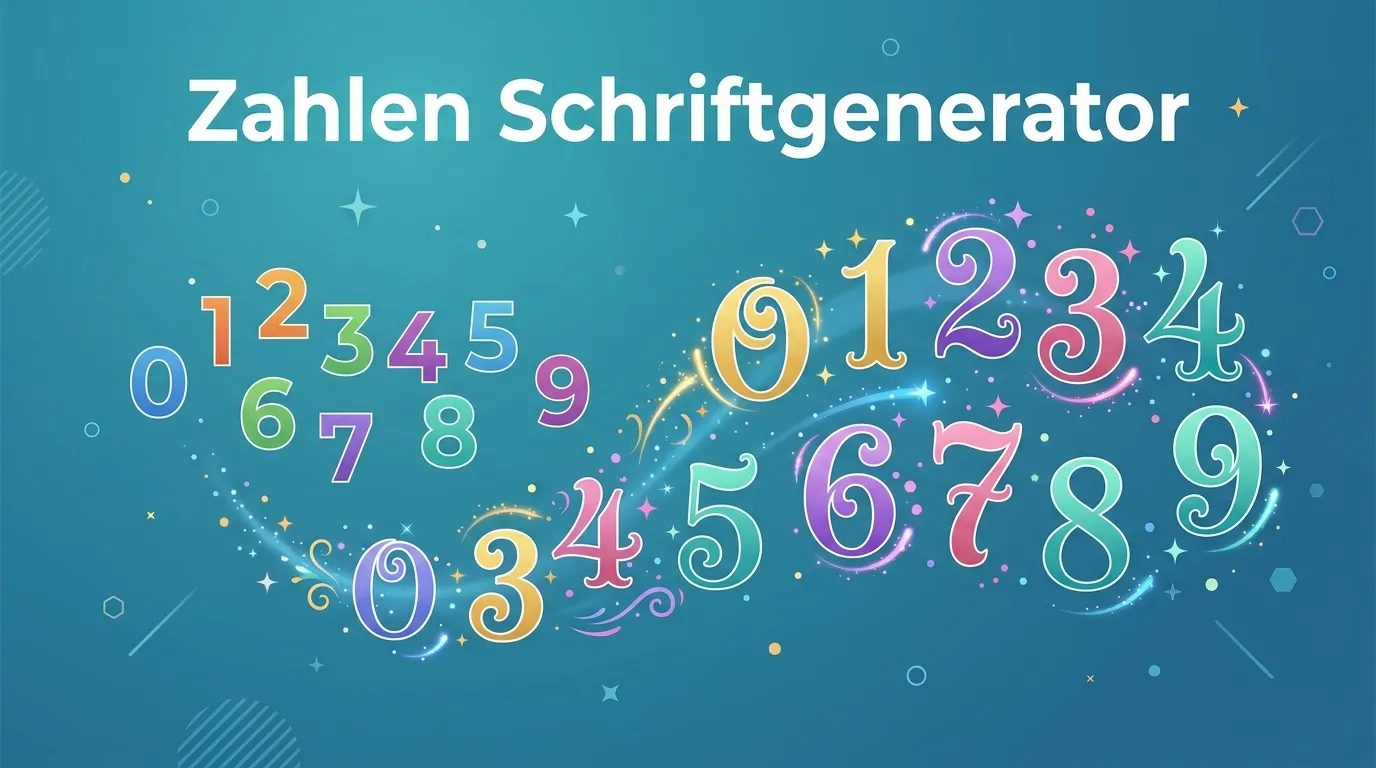
Zahlen Schriftgenerator
Wandle Ziffern in eingekreiste Zahlen, hochgestellte Zahlen, Emoji-Ziffern und weitere coole Stile um: sofort kopierbar für Instagram, WhatsApp und Gaming. Kostenlos, ohne Anmeldung, direkt im Browser.
Barrierefreiheit: Unicode-Sonderzeichen werden von Screenreadern (VoiceOver, TalkBack) oft nicht korrekt vorgelesen. Für zugängliche Websites empfehlen wir semantisches HTML-Formatting statt Unicode-Zeichen.
Zahlen Schriftarten für Instagram, WhatsApp & TikTok
Eingekreiste Zahlen, hochgestellte Ziffern und Emoji-Zahlenstile sind perfekt, um Countdowns, Bestenlisten, Geburtsdaten oder Level-Anzeigen in Social-Media-Profilen hervorzuheben. Unser Zahlen Schriftgenerator wandelt deine Eingabe in Echtzeit um und zeigt dir sofort, wie das Ergebnis auf verschiedenen Plattformen aussieht.
Beliebt sind z. B. ①②③ für nummerierte Aufzählungen in der Instagram-Bio, 𝟏𝟐𝟑 für Gamer-Tags und ¹²³ für wissenschaftliche oder elegante Darstellungen.
Was sind Unicode-Zahlenstile technisch?
Unicode definiert über 150.000 Zeichen: darunter auch verschiedene Darstellungsformen für Ziffern: eingekreiste Zeichen (U+2460 ff.), doppelt gestrichene (U+1D7D8 ff.), hochgestellte (U+00B9, U+00B2, U+00B3) und viele mehr. Diese Zeichen sind echte Text-Zeichen, keine Bilder.
Das bedeutet: Du kannst sie kopieren und überall dort einfügen, wo normaler Text akzeptiert wird. Der Nachteil: Auf sehr alten Geräten oder in Programmen mit eingeschränktem Zeichensatz werden manche Zeichen als Kästchen angezeigt.